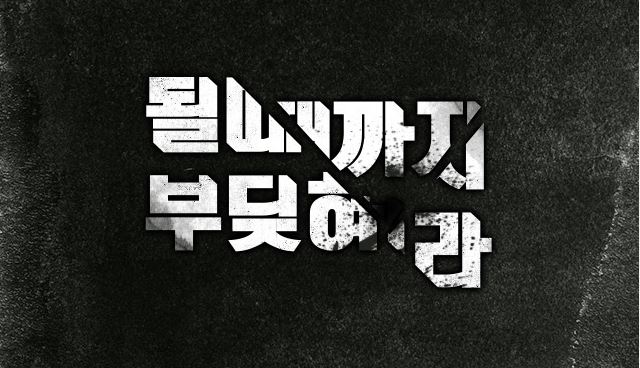
Rix교차로는 넓고 각진 특징으로 교차로를 연상시키는 복고 느낌의 입체적인 제목용 폰트입니다.
넓고 평평하며 네모꼴 안에 꽉 찬 모듈의 복고 서체로 왼쪽 아랫부분에 꺾인 효과를 주어 강한 임팩트를 표현하였습니다. Rix교차로Plus는 오른쪽 윗부분에 꺾인 효과를 한 번 더 주어 입체적인 느낌을 만들었습니다.